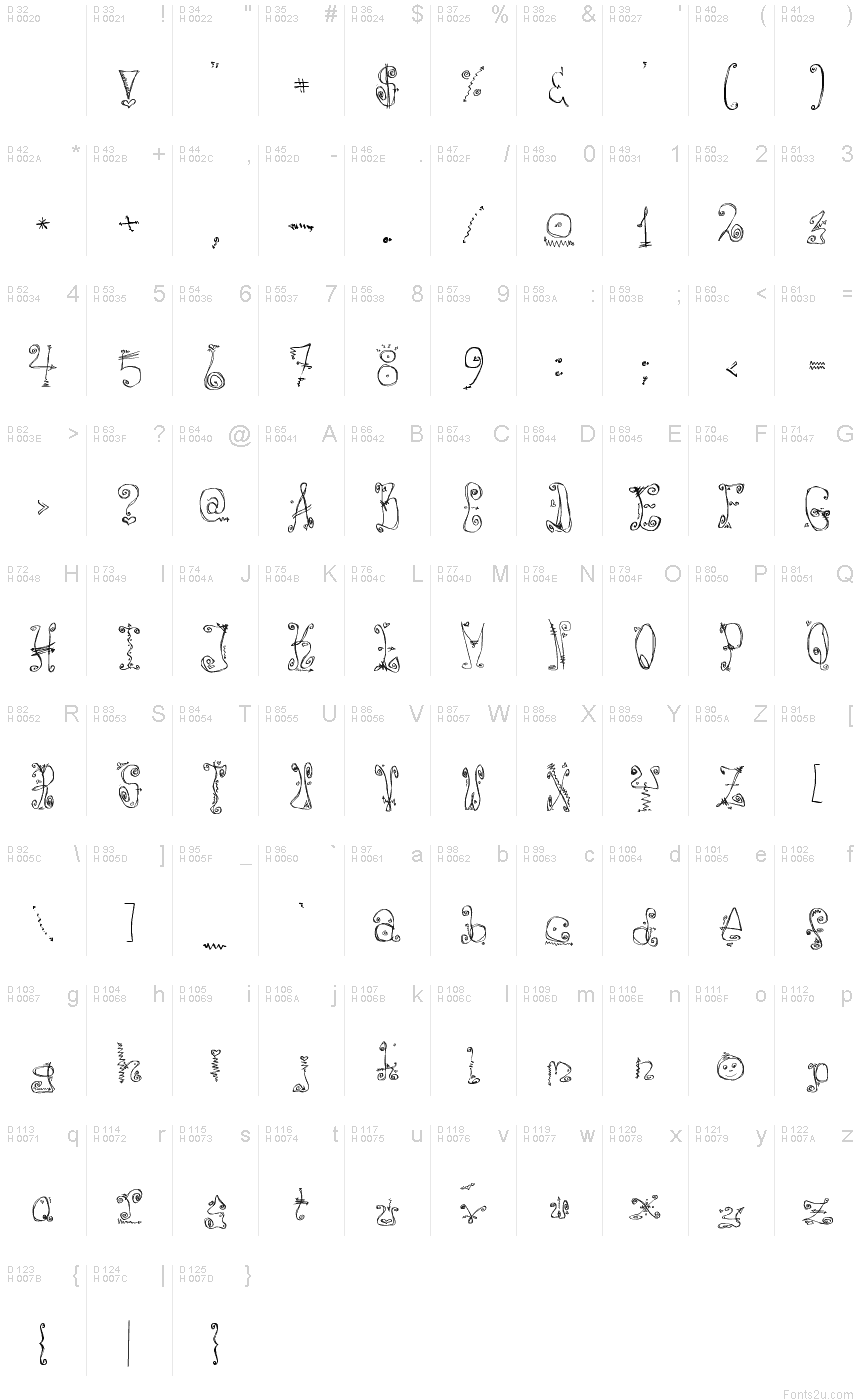
Danzin di Buddha Graphixt è un font display decorativo gratuito con un'energia selvaggia e scribacchiata, che sprigiona tutto il fascino del disegno a mano. Ogni lettera si attorciglia in cappi, spirali e zig-zag, con cuoricini e riccioli che sembrano scarabocchiati sui margini di un quaderno. I tratti sottili e le linee irregolari, quasi abbozzate, le conferiscono una vibrazione giocosa ed elettrica, che cattura l'attenzione senza sembrare impostata o rigida.
Con Danzin, i tuoi titoli diventeranno istantaneamente stravaganti e originali, rendendo questo font gratuito la scelta naturale per inviti a feste, poster per eventi per bambini, fanzine, packaging artigianali, grafiche per social media e biglietti d'auguri particolari. È perfetta usata in grande e in grassetto come titolo, mentre per il testo di accompagnamento suggeriamo un font sans serif arrotondato e semplice per mantenere la leggibilità. Lascia abbastanza spazio intorno alle lettere affinché tutti quei riccioli e cuoricini abbiano spazio per ballare.